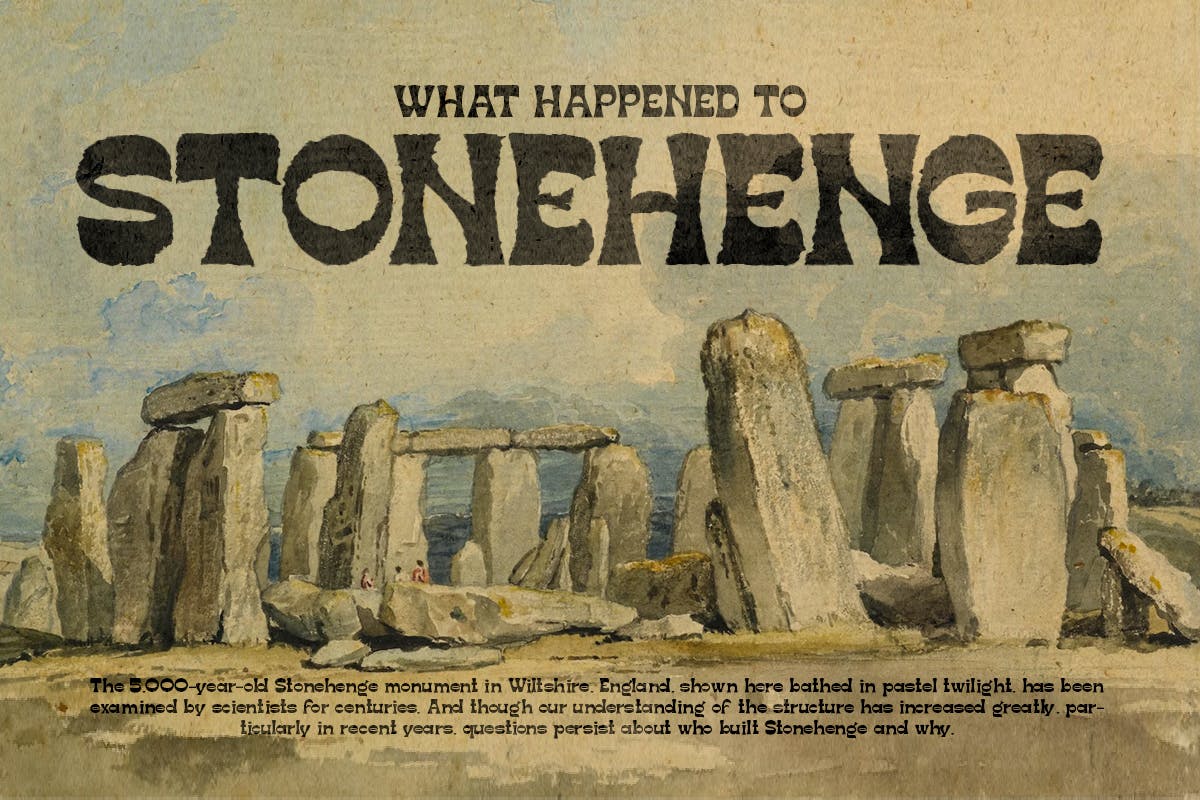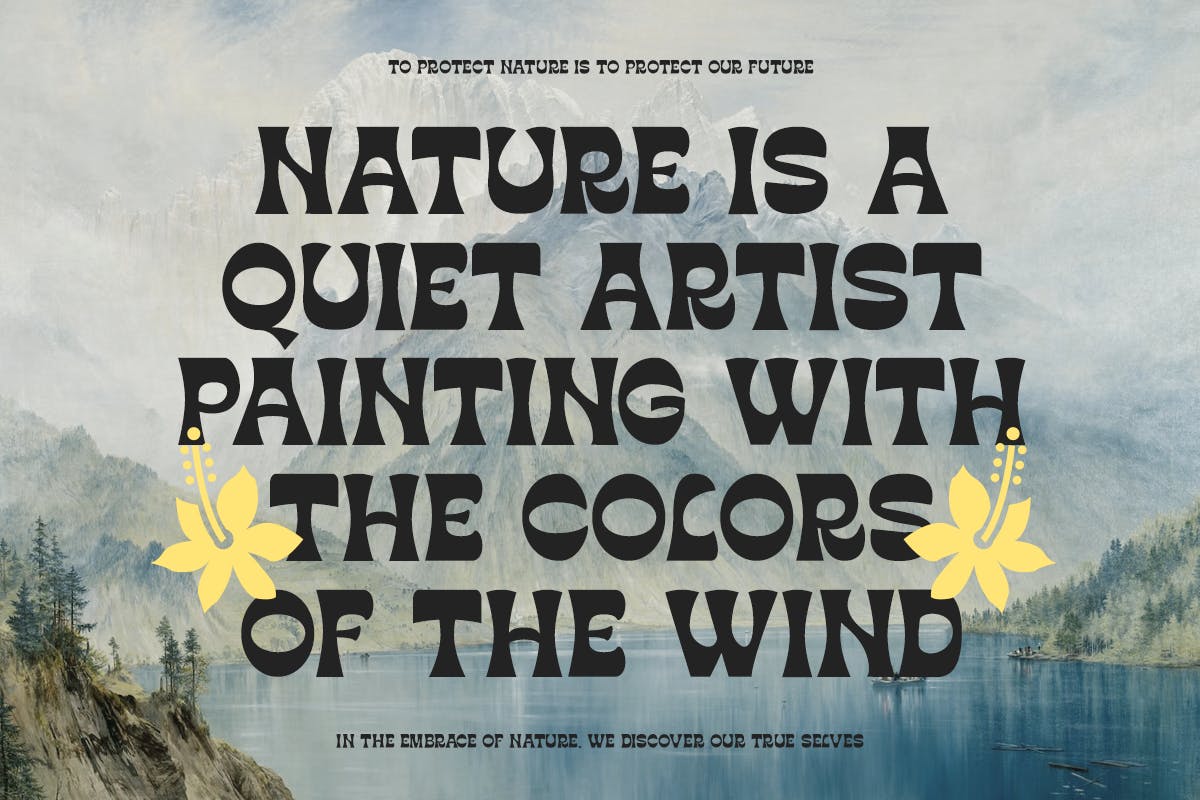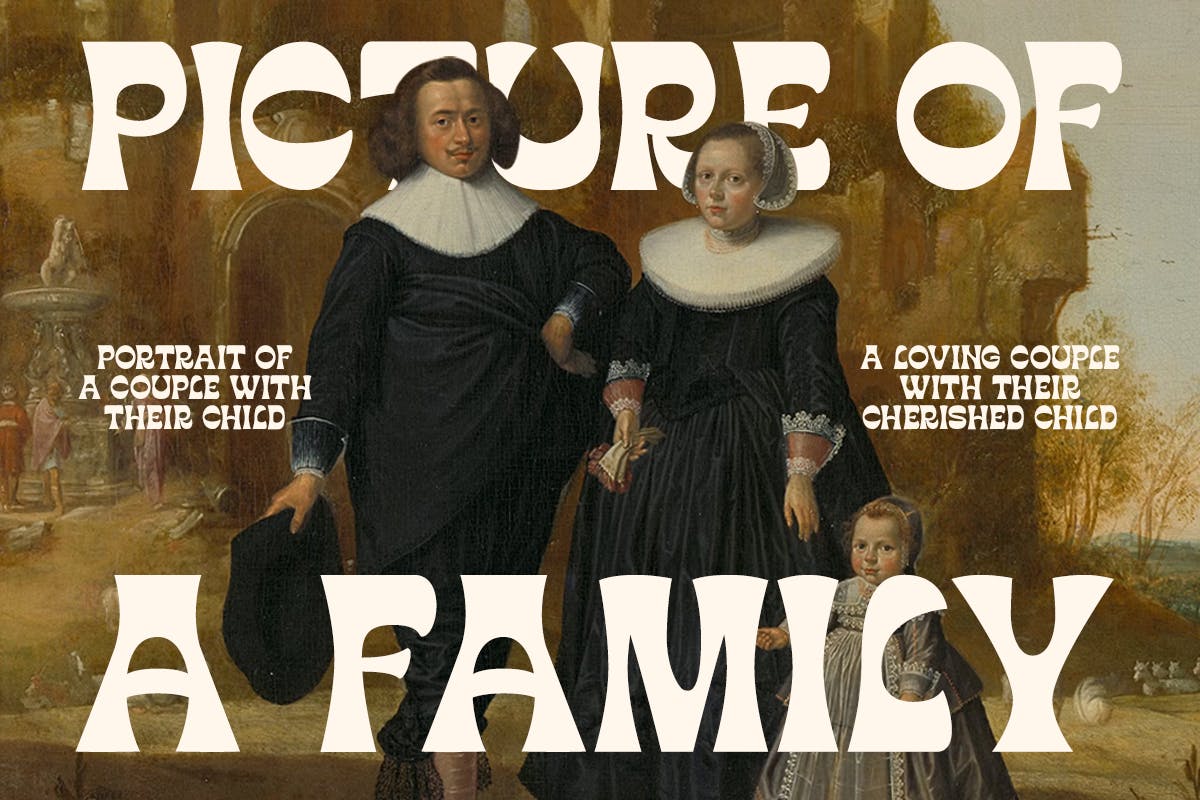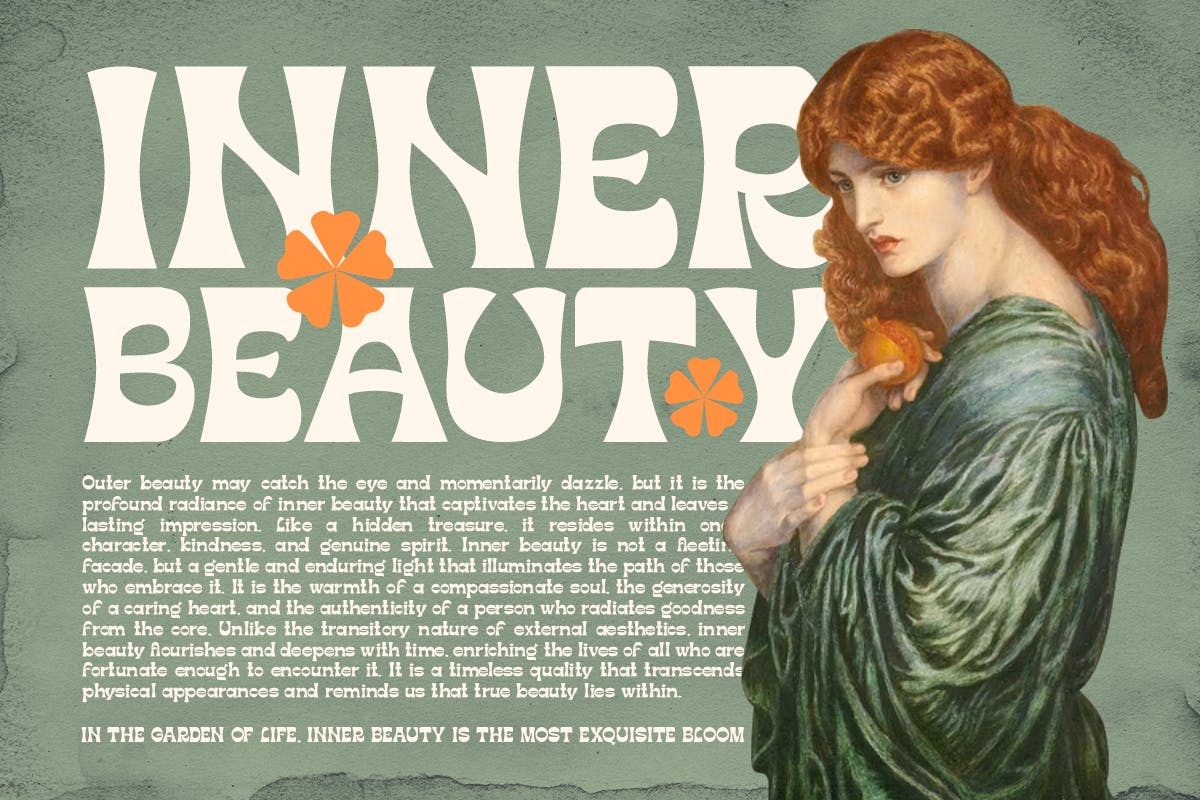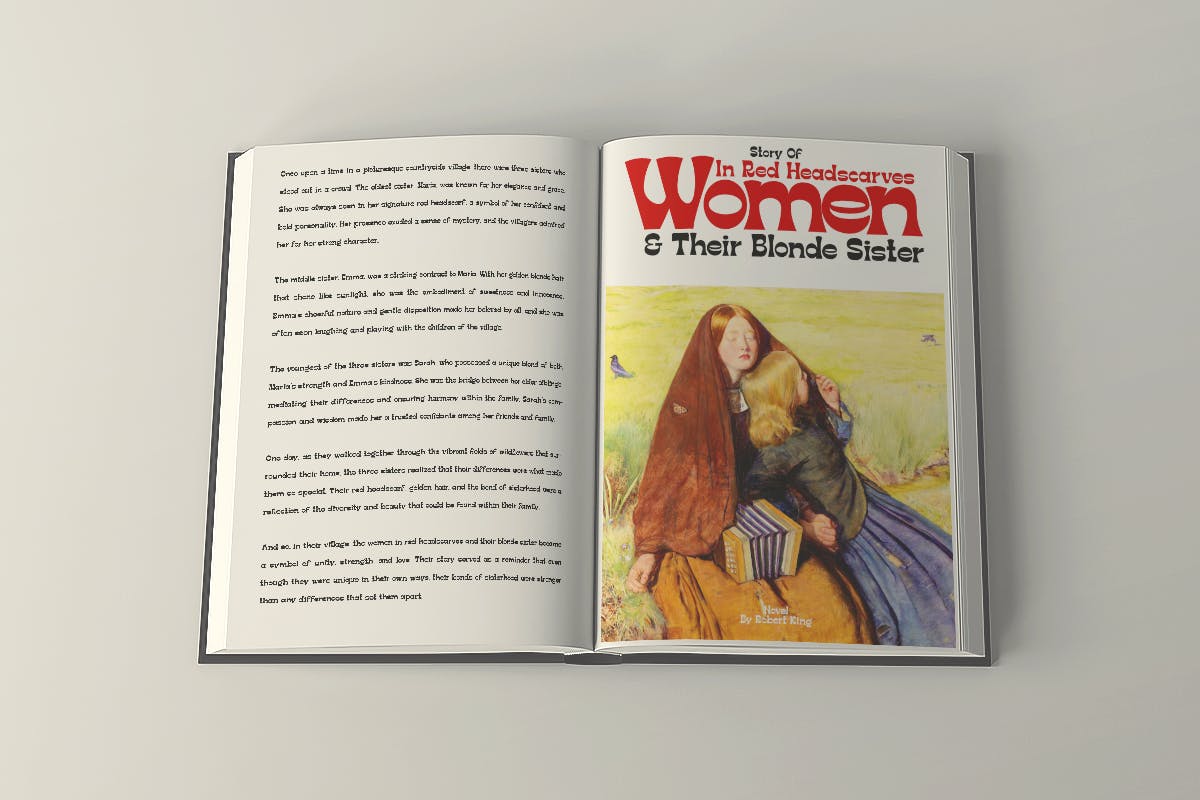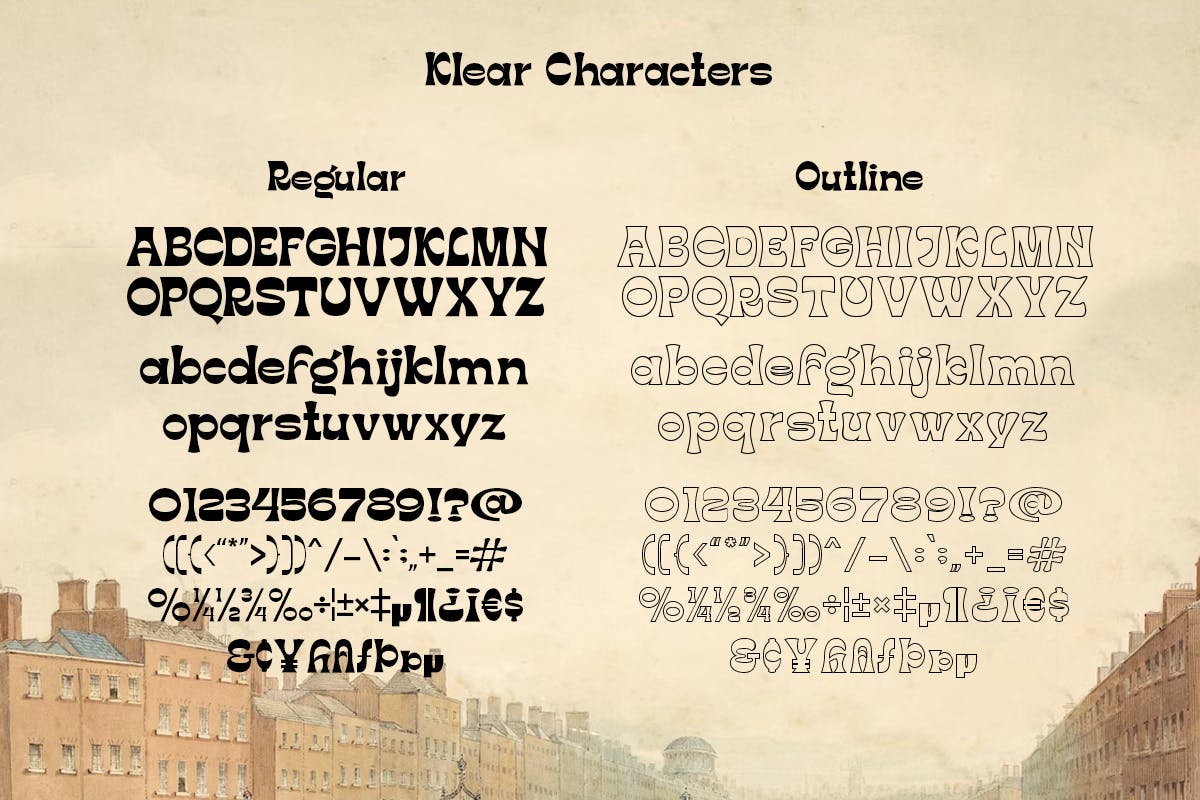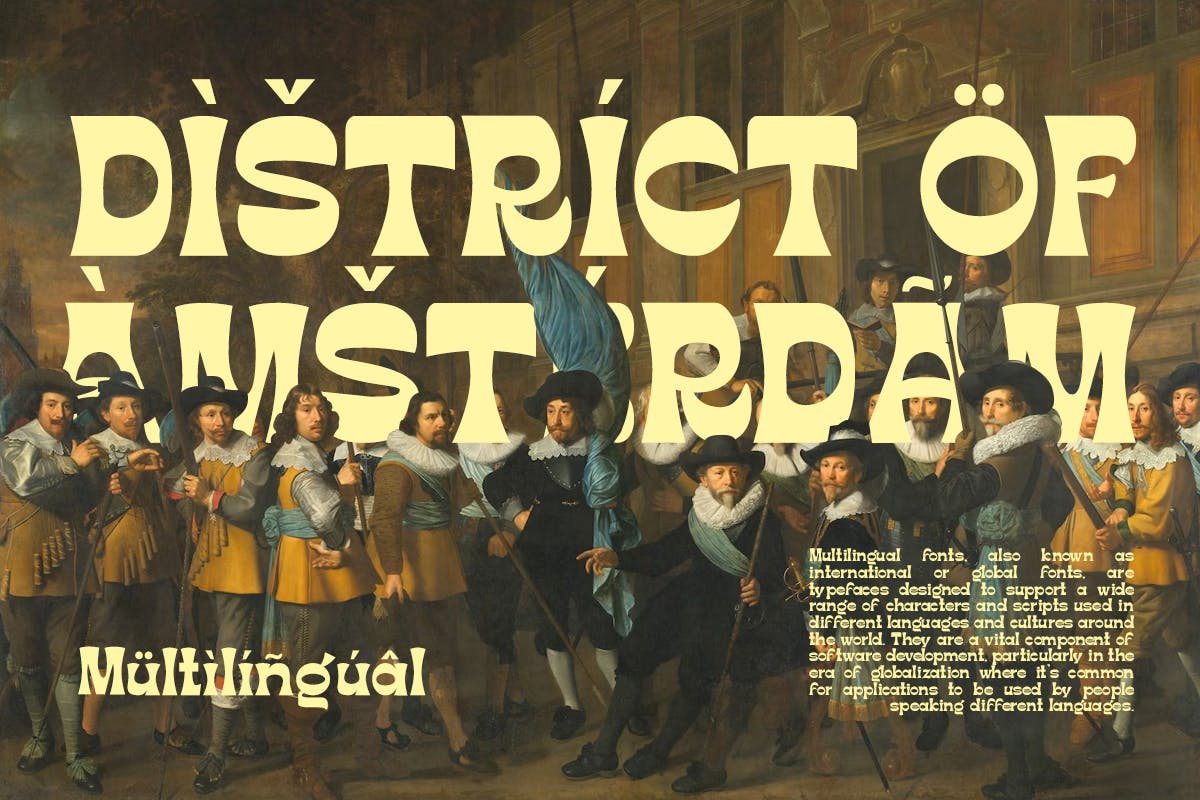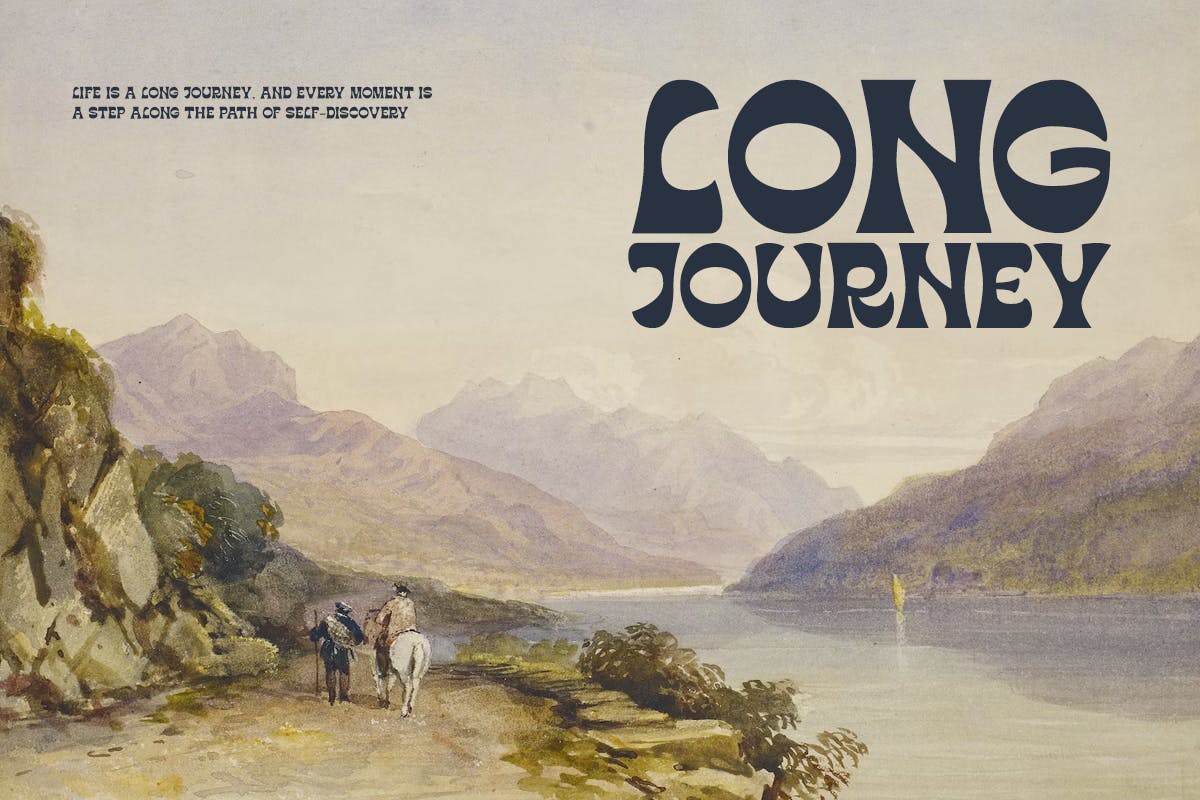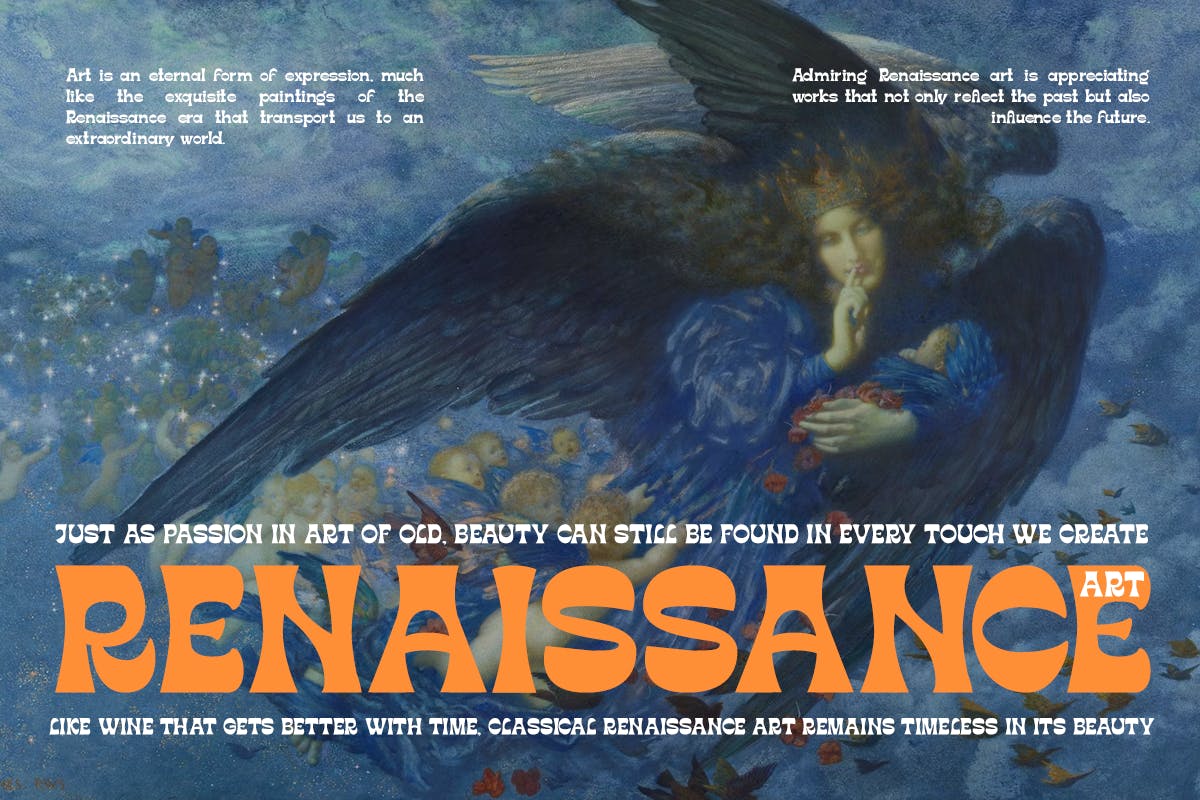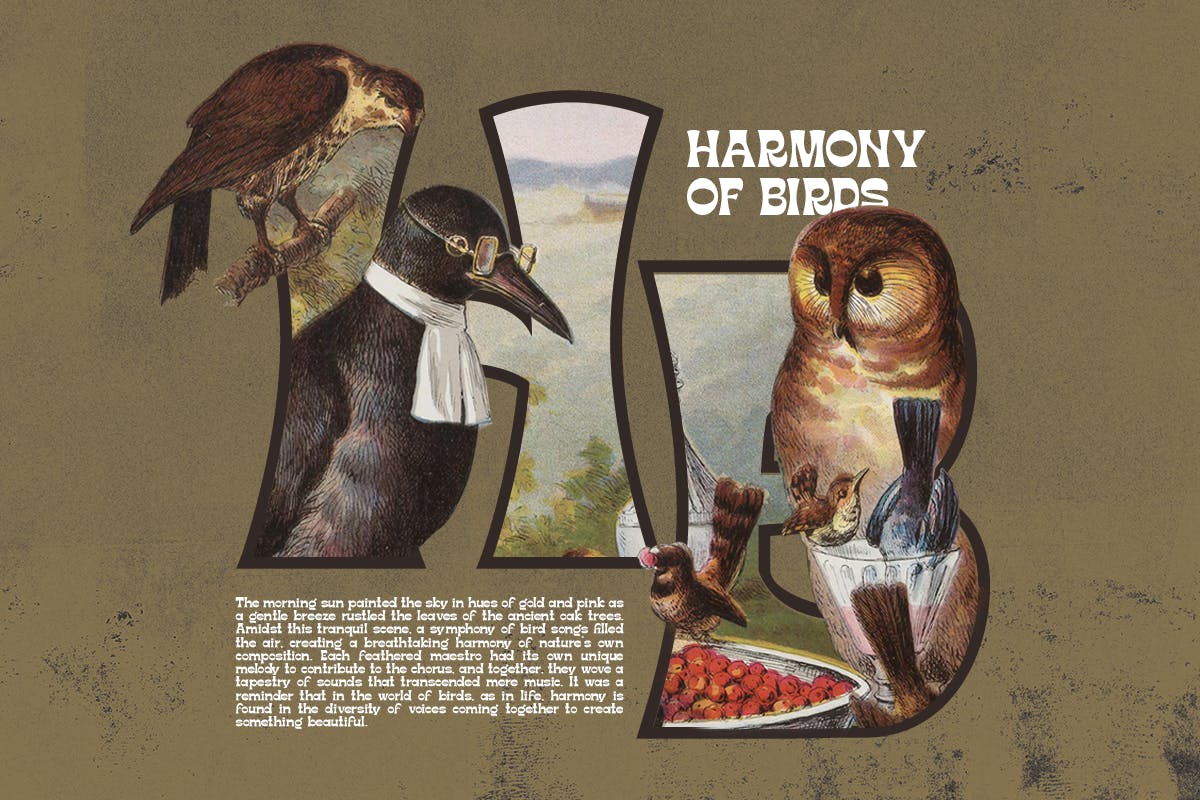
فونت Klear را معرفی میکنیم - یک نوعخط که قواعد طراحی را به چالش کشیده است! الهامگرفته از جریان هنری نو، Klear ترکیبی بینظیر از خاص بودن و زیبایی است.
چه در حال کار بر روی یک پروژه رسمی باشید و چه چیزی بیشتر پیشرو، Klear به شما کمک میکند. با دو سبک انتخابی - Regular و Outline، Klear به خلاقیت شما فضایی تازه برای درخشش میدهد.